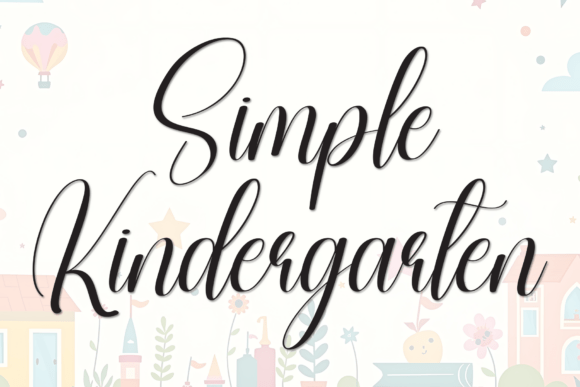
Simple Kindergarten
Việc tìm kiếm các thành phần thiết kế phù hợp có thể là một thách thức, nhưng Simple Kindergarten cung cấp một bộ sưu tập đặc biệt giúp nâng tầm công việc của bạn ngay lập tức.
Được chế tác với độ chính xác cao, Simple Kindergarten cung cấp các vector sạch, kiểu chữ mượt mà và giấy phép thương mại để bạn yên tâm.